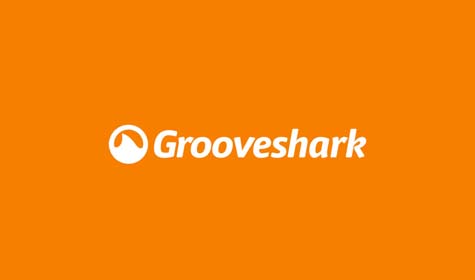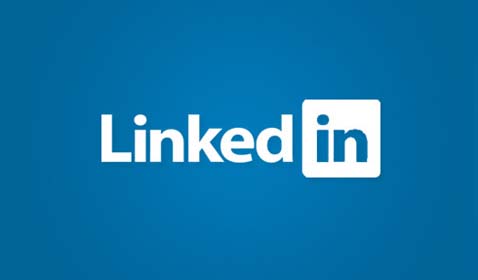
15+ Font Gratis yang Digunakan Pada Logo Brand Terkenal
Font Gratis yang Digunakan Pada Logo Brand Terkenal. Saat Anda bekerja dibidang desain tentu Anda akan dihadapkan dengan situasi yang membingungkan saat memilih font untuk diterapkan pada desain Anda. Bagi sebagian orang yang tidak tahu tentang desain mungkin saja font tidak begitu penting bagi mereka, tapi seorang desainer akan berpikiran berbeda dan menjadikan font berperan sangat penting dalam menunjang desain mereka.
Tapi meskipun Anda bukan seorang desainer profesional, Anda juga harus memperhatikan font untuk membantu kebutuhan desain Anda, atau untuk Anda terapkan pada logo situs Anda, atau untuk Anda terapkan untuk mempercantik tulisan di blog Anda.
Font yang menarik memang sering dijadikan identitas brand bagi sebagian perusahaan besar, mereka mengetahui betapa pentingnya font untuk membangun merek mereka agar terlihat lebih unik, berkesan dan elegan dimata pelanggan. Anda bisa saja memulai dengan membuat logo dari font-font gratis untuk usaha Anda, siapa tahu suatu saat logo Anda menjadi identitas brand untuk perusahaan Anda.
Berikut Font-font gratis yang digunakan oleh Logo Brand Terkenal
Font-font dibawah ini meskipun digunakan oleh perusahaan besar, Anda bisa menggunakan font-font ini untuk kebutuhan pekerjaan Anda sehari-hari, juga bisa Anda gunakan sebagai inspirasi dalam pemilihan font untuk desain Anda.
Facebook adalah media sosial terbaik di dunia saat ini dan paling banyak digunakan oleh orang diseluruh dunia. Facebook mempunyai logo yang sederhana dan unik sebagai identitas mereka. Dan untuk logo facebook, mereka ternyata menggunakan font gratis yang bernama Klavika Bold.
Font klavika adalah font yang sederhana dan berfokus pada ruang dan geometri yang besar. Aspek konektivitas benar-benar terlihat yang menggambarkan tujuan dari Facebook.
Google adalah mesin pencari yang digunakan oleh hampir setiap pengguna internet di dunia ini, dengan kemampuan menghasilkan pencarian informasi terbaik menjadikan google menjadi mesin pencari terbaik dunia.
Google mungkin menjadi perusahaan yang sangat sering mengubah font. Dan saat ini google menggunakan font gratis juga yang bernama Catull BQ.
Font Catull BQ ini merupakan font yang cukup mengesankan dan memberikan tepi yang diperlukan untuk logo Google.
Adidas
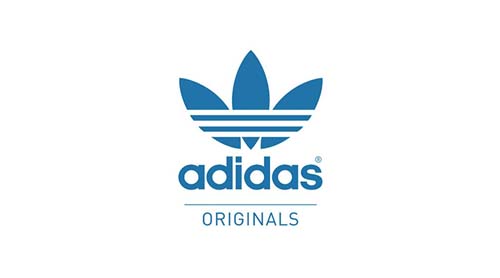
Adidas adalah perusahaan yang menyediakan berbagai macam kebutuhan alat untuk olahraga, dan adidas telah berhasil menunjukkan kepada dunia bagaimana membangun merek olahraga yang baik. Bahkan adidas terkenal di kalangan pecinta olahraga dan pengguna secara merata diberbagai belahan dunia.
Adidas menggunakan font ITC Avant Garde Gothic Medium. Font ini merupakan font yang mengesankan dan dapat menjadikan logo adidas terlihat sederhana dan intuitif.
IBM
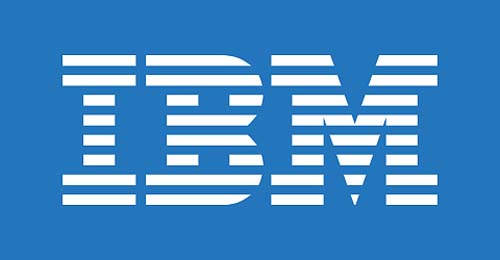
IBM adalah perusahaan dibidang teknologi komputer yang sudah memberikan kontribusi besar dalam memenuhi kebutuhan semua orang dan menjadikan pertumbuhan teknologi berkembang dengan pesat.
IBM menggunakan font gratis terkenal custom-made bernama IBM font. Dan, Anda saat ini juga dapat menggunakannya untuk proyek desain Anda juga.
The New York Times
The New York Times merupakan media berita besar yang terkenal dan mereka menggunakan font English Towne gratis untuk logo mereka. Font ini sangat mengesankan dan menggunakan karakter melengkung untuk memberikan tampilan font penuh.
Font ini memang terlihat lebih unik dan menjadikan New York Times mempunyai ciri khas di mata pembaca.
Digg
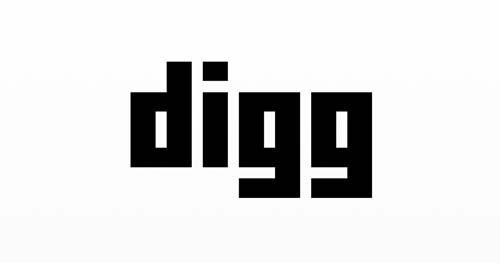
Digg adalah agregator berita populer yang menggabungkan semua berita dan artikel yang terbaik, yang bisa Anda lihat pada portal mereka. Digg sangat populer dan memiliki jutaan pengguna di situs web mereka.
Digg juga menggunakan font gratis Pico Y. Karakter huruf tidak memiliki kurva dari jenis apa pun. Semua sisi font dibuat tajam 90 derajat untuk memberikan kesan hidup kepada masing-masing karakter. Logo final Digg terlihat baik dan menarik.
YouTube
YouTube adalah situs berbagi video terbesar dan populer di dunia saat ini, youtube menjadi sangat besar setelah dibeli oleh google. Youtube menggunakan font gratis bernama League Gothic Regular, font ini menjadikan logo youtube terlihat tegas dan tajam.
Envato
Envato adalah Digital marketplace yang menjual berbagai macam aset kreatif seperti desain web, audio, video, tema, gambar, fotografi dan masih banyak lagi. Situs ini menjadi tempat mendulang dollar bagi para desainer diseluruh dunia. Envato dalam logonya menggunakan font Ubuntu Italic, font ini membuat brand envato terlihat sangat cantik.
Engadget
Engadget adalah situs yang membahas dunia teknologi secara lengkap dan ini merupakan situs yang juga sangat terkenal, Engadget juga membahas secara detail terkait dengan teknologi sehingga mereka dapat menyajikan informasi teknologi yang terbaik untuk pengguna.
Engadget menggunakan font bernama The Engadget Font (tapi ini merupakan font yang hampir mirip, meskipun ini bukan jenis font asli yang Engadget gunakan).